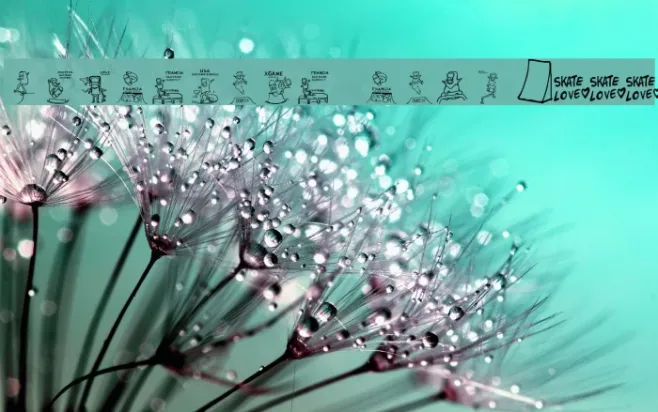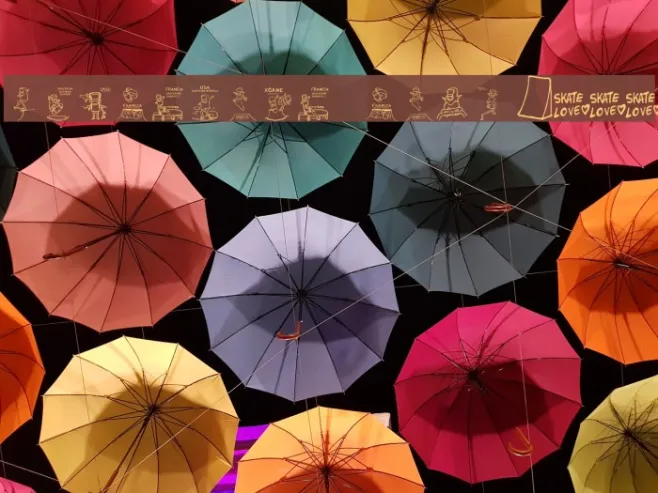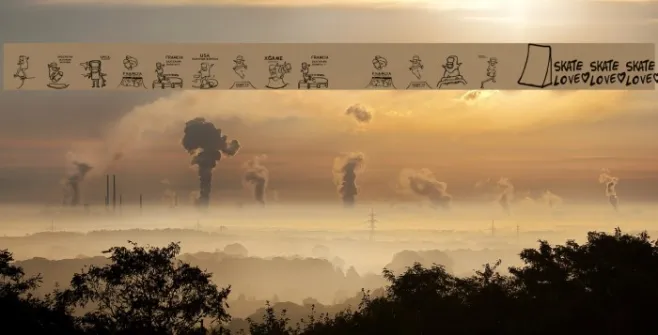
skatelove [ tour 2009] Font
Fonts by Rodrigo German - RASDESIGN
| Style général | Playful, Youthful, Urban, Decorative |
| Cas d'utilisation | Logos, Headlines, Posters, Merchandise |
| Projets proposés | Youth event posters, skateboarding brands, streetwear logos, social media graphics, informal invitations. |